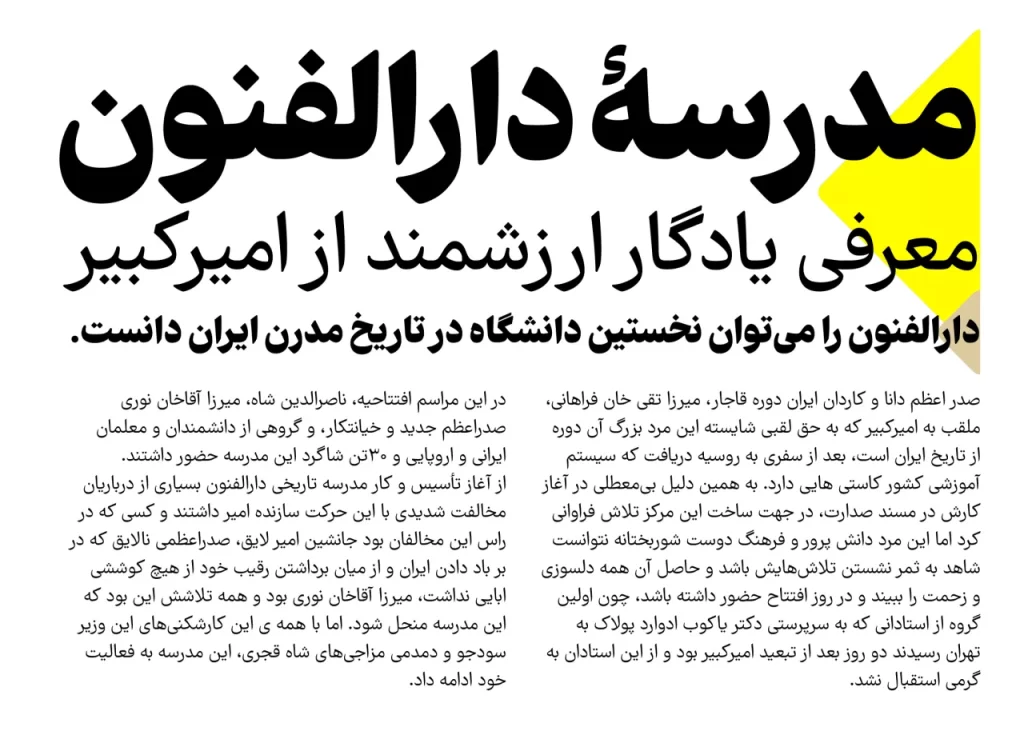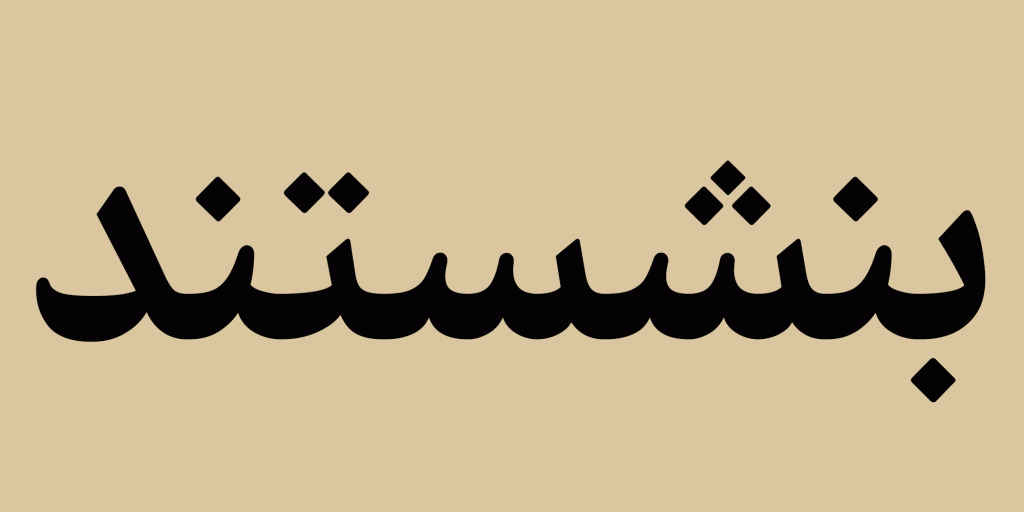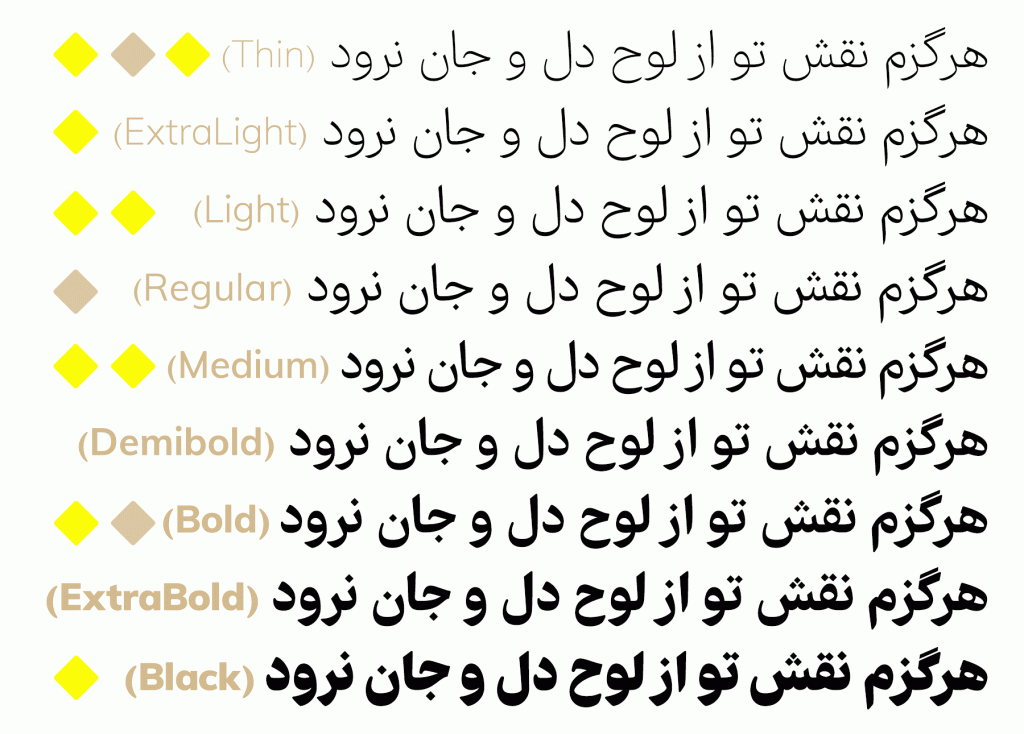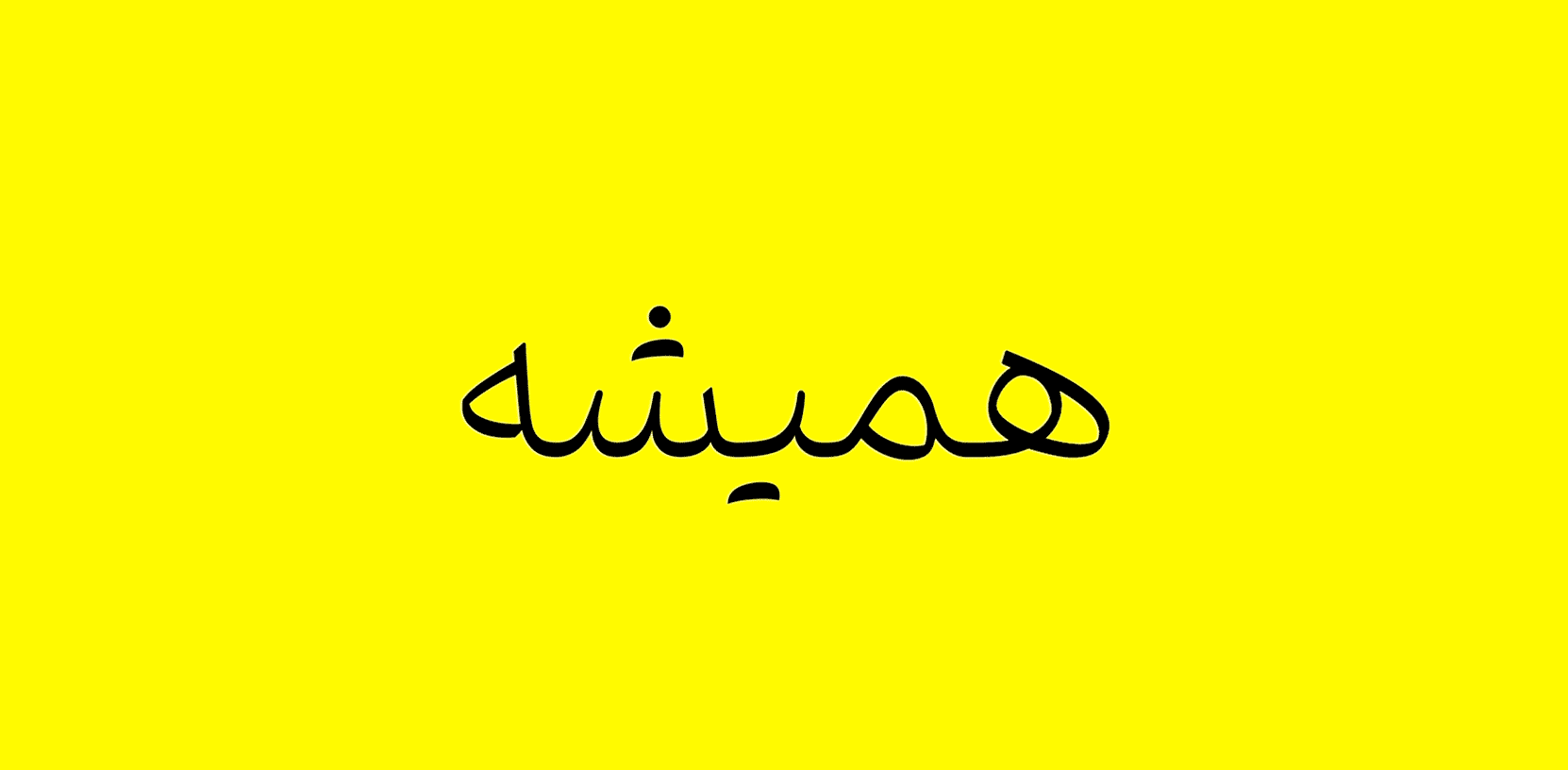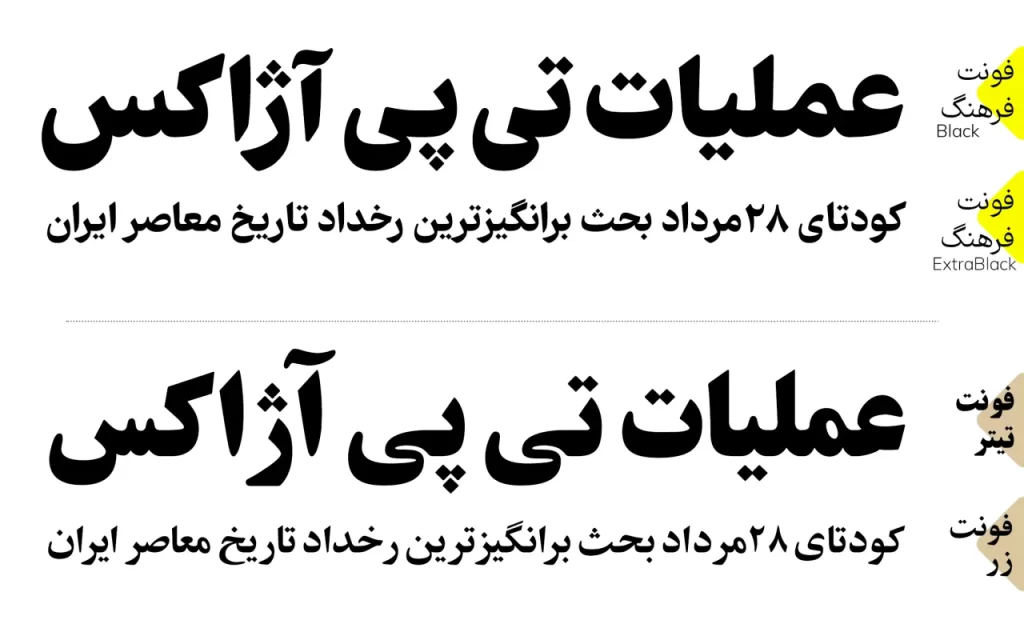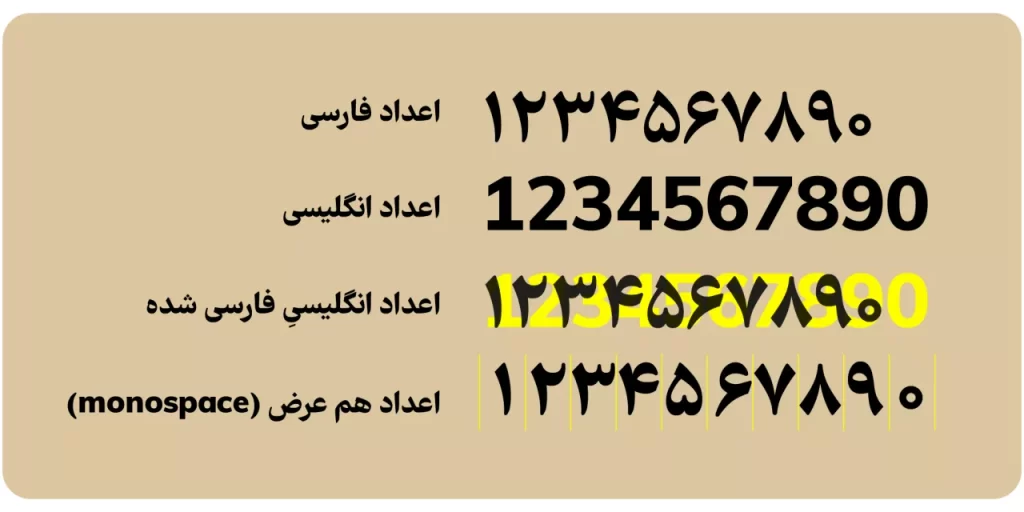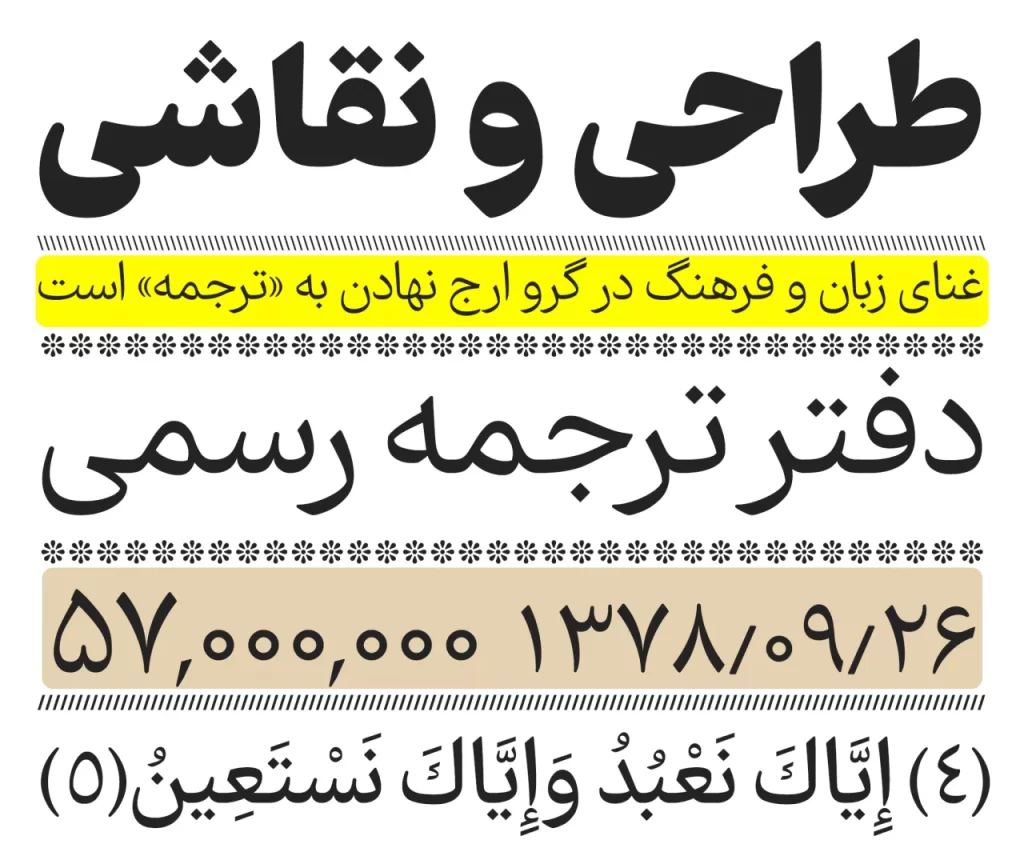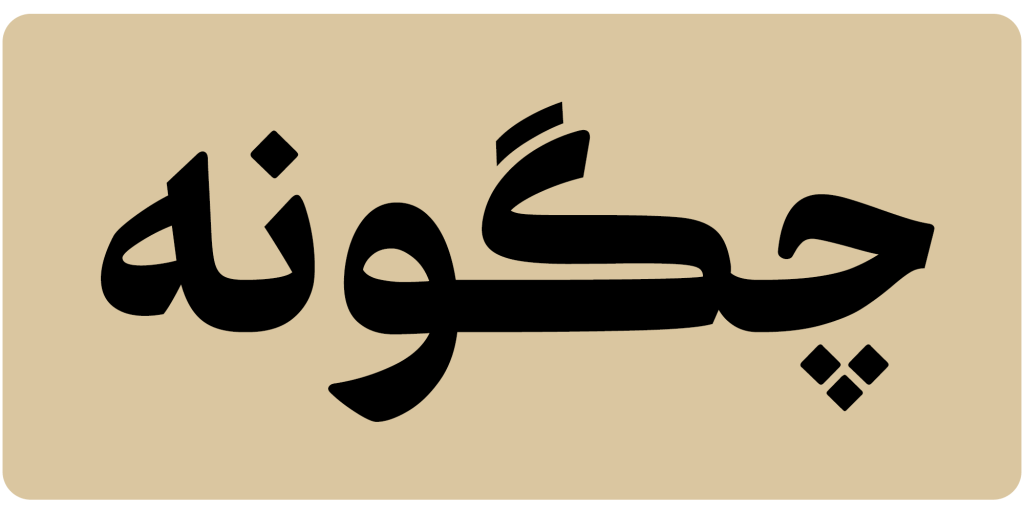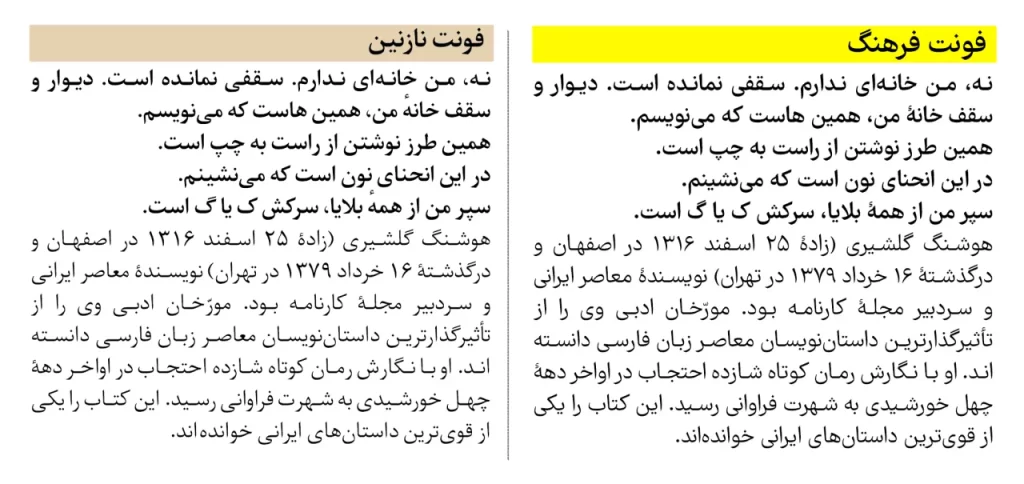
فونت فرهنگ
فونت فرهنگ نسخه ای به روز شده از تایپ فیس های قدیمی و مشهور تایپوگرافی ایران است. به ندرت افرادی را می توان یافت که اندکی با تایپ و تایپوگرافی آشنا باشند و نام تایپ فیس های زیبا و مشهور نازنین زر و تیتر را نشنیده باشند. حسین عبدالله زاده حقیقی در دوران پهلوی با کمک تکنولوژیهای اولیه و ماشینهای چاپ قدیمی این فونت های زیبا را طراحی و خلق نمود.
پر واضح است که هر روز تکنولوژی در مسیر پیشرفت خود است و تایپوگرافی هم در مسیر پویایی و رشد خود قدم بر می دارد. از همین رو به واسطه همین اصل ایده طراحی و بازسازی این تایپ فیس های زیبا سبب خلق قلم فرهنگ شد. فرهنگ با با حفظ اصول طراحی قلم های مذکور از جمله استفاده از دور و منحنیهای زیاد، برشهای گرد و شکستگیهای محدود و … ایجاد و متولد گردید
تنوع اوزان و حالت های مختلف نقطه گذاری
خانواده فرهنگ دارای 9 وزن متفاوت از ظریف تا خیلی ضخیم است. تنوع گسترده در اوزان قلم فرهنگ نقطه مقابل تایپ فیس قدیمی است که دارای یک یا نهایتا 3 وزن بوده اند. همچنین با دارا بودن نسخه متغییر یا variable سبب کاهش حجم و افزایش سرعت بخصوص در وب سایت ها وشبکه های اجتماعی می شود. یعنی تمامی اوزان کشیدگی تنوع نقطه ها و ترکیبات جایگزین در یک فایل varible موجود است.
در این تایپ فیس دو نوع شکل نقطه گذاری معمولی و نقطههای گرد و پیوسته طراحی شده است. جایگذاری نقطه ها در تایپ فیس فرهنگ ایده آل است. محدودیت های حروف چینی در دستگاه های چاپ قدیمی سبب خوانایی نامطلوب حروف های نقطه دار بوده است. در این تایپ فیس (Farhang) با توجه به تکنولوژی به روز طراحی هر دندانه با توجه به حروف قبل و بعد خود جای نقطهٔ خود را طوری تعیین میکند تا نهایت نظم و زیبایی در شکل کلمات بدست آید.
ترکیبات جایگزین در تایپ فیس فرهنگ
در تایپ فیس فرهنگ لیگچرها و ترکیبات جایگزین متعددی طراحی شده است. تا سبب خلق تنوع و زیبایی بیشتری برای نوشته ها گردد. همچنین دست طراحان را برای تنوع بخشی بر اساس سلیقه باز گذاشته است.پس از دانلود این محصول می توانید این حروف جایگزین را طبق راهنمای آن استفاده نمائید.
این فونت از زبان فارسی، عربی، کردی، اردو و انگلیسی پشتیبانی میکند.